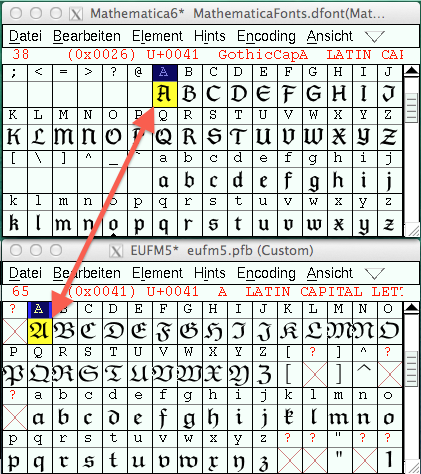
ich würde gerne in einer Schrift "Mathematica6" im pfb Format das Zeichen, dass dem A auf der Tastatur zugeordnet ist, durch ein Zeichen aus einer anderen Schrift "EUFM5" ersetzen. Ich habe mir dazu das Programm Fontforge heruntergeladen und installiert, bekomme aber nun einfach nicht hin den einen Buchstaben aus "EUFM5" zu exportieren und ihn in die Schrift "Mathematica6" wieder einzufügen.
Wie mache ich das am besten?
Ganz davon abgesehen, dass du damit einen komplett stilfremden Buchstaben in die Schrift einbauen würdest, das garantiert nicht gut aussieht, ist das auch ein Verstoß gegen die Schriftlizenz. Trotzdem ist das doch eigentlich recht simpel: Doppelklick in der einen Schrift, die komplette Kontur markieren, und kopieren, dann in der anderen Schrift auch Doppelklick um ins Glypken-Bearbeitungsfenster zu kommen, da erst die ungewünschte Kontur markiere und löschen, und die Kontur aus der Zwischenablage einfügen, eventuell Größen korrigieren.
Ich würde mir aber eher aus der Zielschrift ein passendes A zurechtbauen, als dort eines mit dem dort total unpassenden Elefantenrüssel hinein zu mogeln. Das könnte man z.B. einigermaßen in der Form passend aus dem U fertigen. Auf alle fälle besser als ein Zwiebelfisch.
Danke, aber das mit dem copy and paste funktioniert bei mir nicht. Vielleicht habe ich eine beschädigte version von fontforge. Habe das jetzt aber hinbekommen indem ich den Buchstaben als eps exportiert habe, und dann wieder im "Zeichnen-Modus" importiert habe.
Wie kann ich denn die Größe eines Buchstabens im "Zeichnen-Modus" ändern? Ich habe jetzt einfach die Größe der Schrift aus der ich den Buchstaben nehme bei der Schrift-Information auf die Größe der Zielschrift eingestellt und dann den Buchstaben exportiert und eingefügt. Kann man das auch direkt im Editor machen?